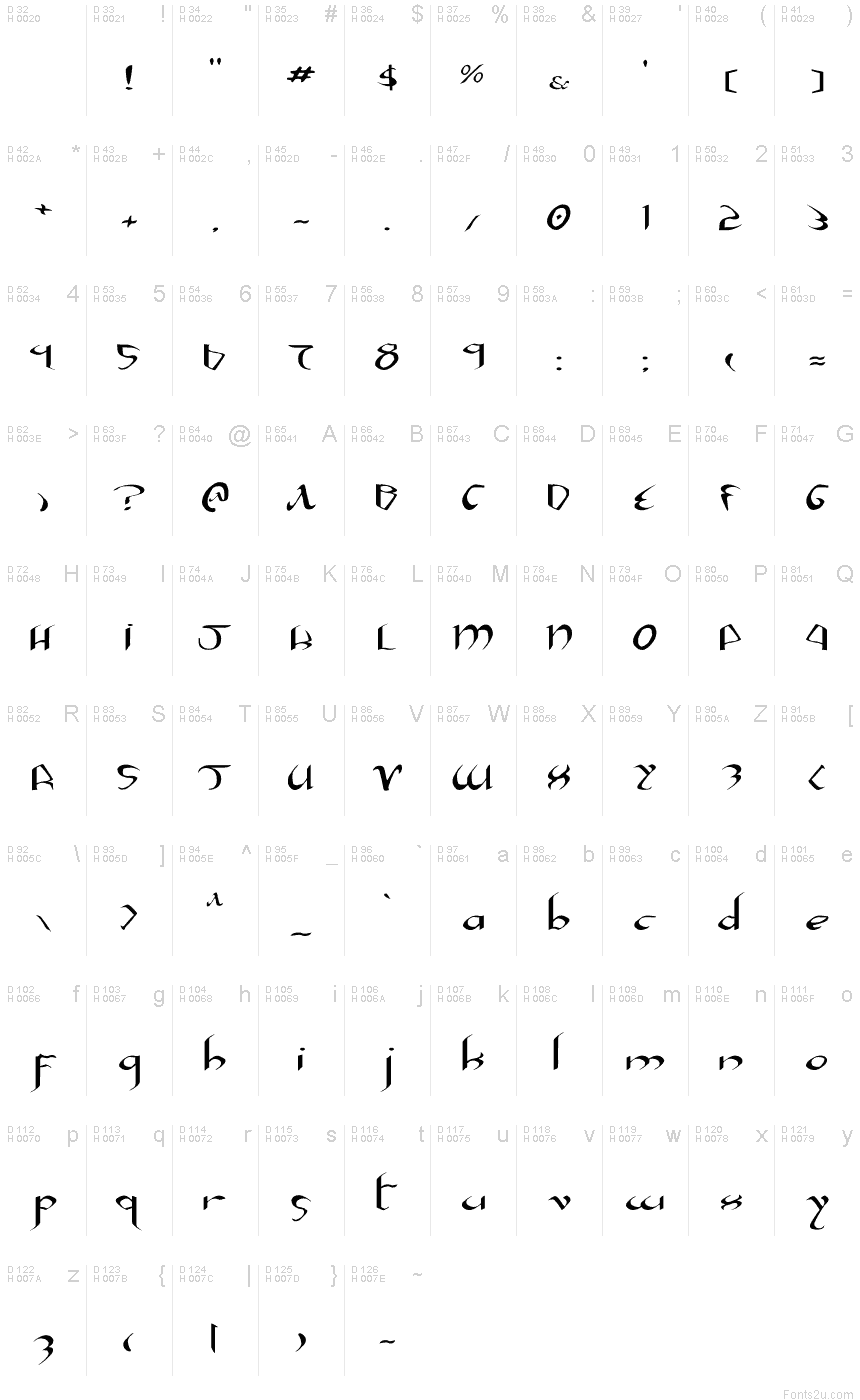
Anteprima del carattere Xaphan II Expanded
Xaphan II Expanded, di Iconian Fonts, è un font gratuito in stile gotico celtico dal ritmo netto e oscuro. Le lettere richiamano le convenzioni della blackletter medievale, ma le curve sono più fluide che austere, con punte a uncino, tratti spezzati e aste arrotondate che ne ammorbidiscono la struttura.
Perfetto per copertine fantasy, loghi di giochi, grafiche per band, insegne di pub e titoli di capitoli che richiedono un tocco di drammaticità d'altri tempi. Essendo gratuito, è ideale anche per brevi linee su poster o iniziali in stile monogramma, poiché gli spuntoni affusolati e le curve decise donano a ogni lettera un fascino cerimoniale ed araldico.